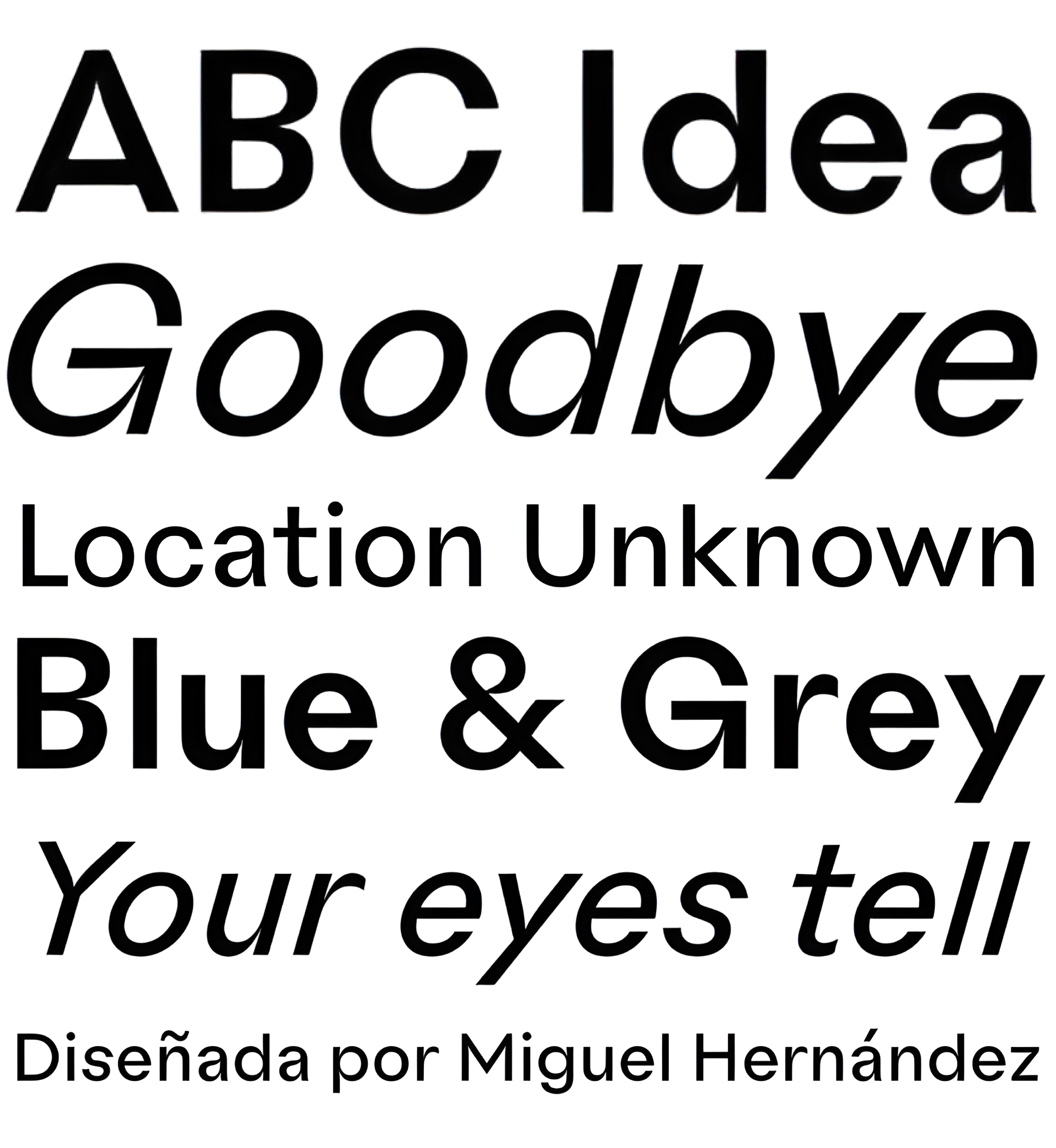
| Créditos | Miguel Hernández |
| Descripción | ABC Idea es una sans geométrica contemporánea llena de características opentype en Regular, Negrita y Cursiva muy «rápida». |